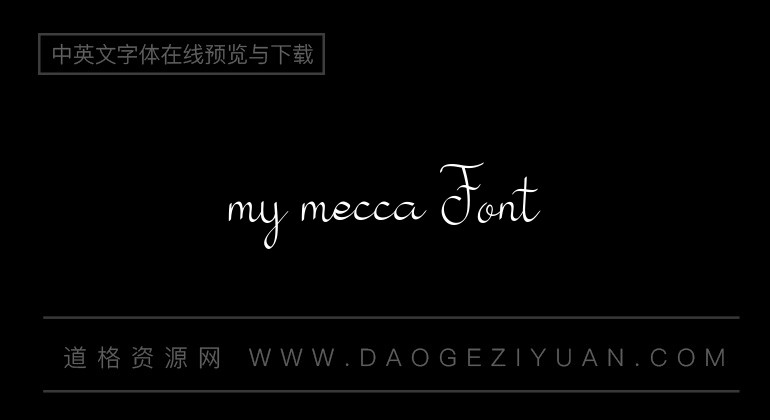
my mecca Font
My Mecca Font 是一款免费提供下载的手写风格英文字体。这个字体的名字来源于伊斯兰教最重要的圣地麦加。 该字体的特点是具有手写体的风格,线条流畅、舒适,适用于许多场合,如个人博客、网站设计、广告和海报等。它有三种字重可供选择,包括 Regular、Bold 和 Light。 My Mecca Font 可以免费用于商业和个人项目,可在不同的平台上使用,包括 PC、Mac、Linux 和移动设备。使用 My Mecca Font 可以为你的设计增添一份独特的风格和个性。
my mecca Font是一款非常不错的手写艺术字体,具有很好的视觉感,适合于文化类的宣传设计、商业类品牌的广告和产品包装设计以及个性化文字排版等较多场景。